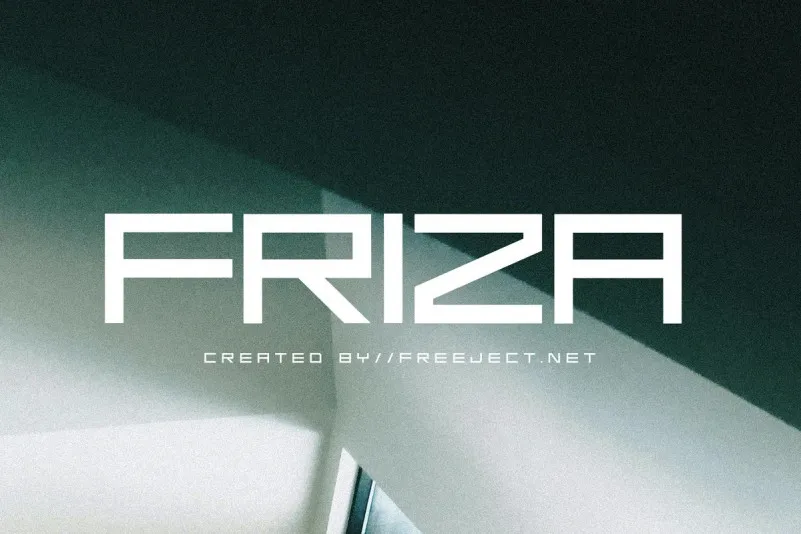
Friza Font – Download Grátis
Esta é uma fonte criada pela freeject.net Design e está disponível sob termos de uso gratuito. Foi projetada especificamente para espaços com espaço apenas na caixa alta, com um formato rígido que tem ângulos quadrados e um aspecto geométrico. É uma fonte firme e poderosa, que cria um impressionante visual. Seu design é perfeito para representar temas futuristas e pode ser classificada como uma fonte de exibição, pois é ideal para destacar e criar algo diferente. É excelente para uso em títulos, logomarcas, panfletos e fontes de destaque. Embora seja principalmente projetada para ambientes que valorizam uma aparência moderna e inovadora, esta fonte também se encaixa bem para promover temas como tecnologia mais recente ou observação espacial. A sua versão em caixa alta oferece um contraste visual interessante que pode atrair atenção e tornar o seu anúncio fácil de ser visto. Em resumo, esta fonte é ideal tanto para usar em propagandas quanto em design gráfico moderno, projetado para destacar e promover novas ideias.